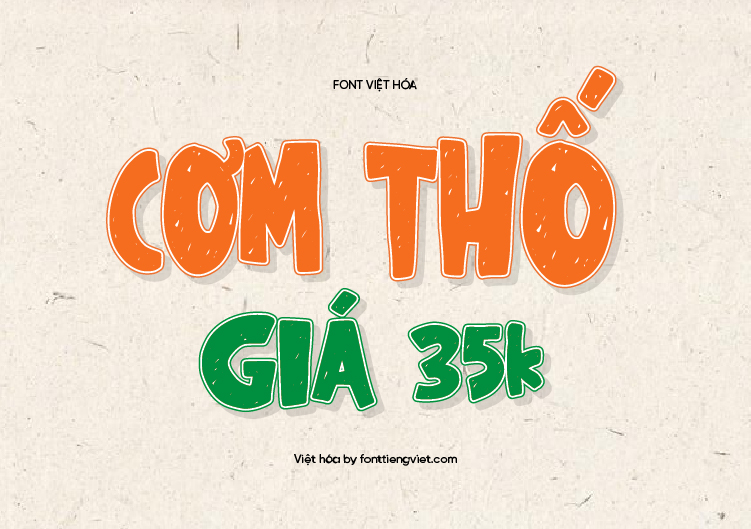
Font Việt hóa 1FTV VIP Sketchy in snow
Giới thiệu về bộ Font Việt hóa 1FTV VIP Sketchy in snow
Chào mừng các bạn đến với thế giới sáng tạo đầy màu sắc dành cho học đường. Nếu bạn đang tìm kiếm một làn gió mới cho các bài thuyết trình hay báo tường, Font Việt hóa 1FTV VIP Sketchy in snow chính là sự lựa chọn hoàn hảo nhất. Đây là một mẫu Font Miễn Phí mang phong cách vẽ tay độc đáo, kết hợp cùng hiệu ứng những bông tuyết nhỏ xinh đậu trên từng nét chữ. Bộ font này không chỉ giúp nội dung trở nên sống động mà còn gợi lên cảm giác ấm áp, gần gũi trong những ngày đông giá rét, rất phù hợp cho các dự án nghệ thuật của học sinh và giáo viên.
Đặc điểm nổi bật của phông chữ Sketchy in snow
Điểm ấn tượng nhất của bộ chữ này chính là sự tỉ mỉ trong từng đường nét phác thảo (sketch). Các ký tự được thiết kế với độ dày vừa phải, không quá cứng nhắc mà vô cùng linh hoạt. Đặc biệt, phiên bản này đã được việt hóa hoàn chỉnh, giúp các bạn sử dụng tiếng Việt có dấu một cách mượt mà, không lo lỗi hiển thị hay mất nét chữ. Những bông tuyết trắng muốt trang trí quanh chữ cái tạo nên một không gian mùa đông kỳ diệu ngay trên trang giấy hoặc màn hình máy tính của bạn.
Ứng dụng Font Việt hóa 1FTV VIP Sketchy in snow trong học tập
Các bạn học sinh có thể sử dụng bộ font này để làm thiệp chúc mừng Giáng sinh, thiết kế bìa tiểu luận hoặc trang trí các slide bài giảng thêm phần cuốn hút. Giáo viên cũng có thể dùng nó để tạo ra các phiếu bài tập sinh động, giúp học sinh cảm thấy hứng thú hơn khi học tập. Sự kết hợp giữa nét vẽ tay mộc mạc và chủ đề tuyết rơi mang lại vẻ đẹp tinh tế, chuyên nghiệp nhưng vẫn giữ được nét hồn nhiên đúng lứa tuổi.